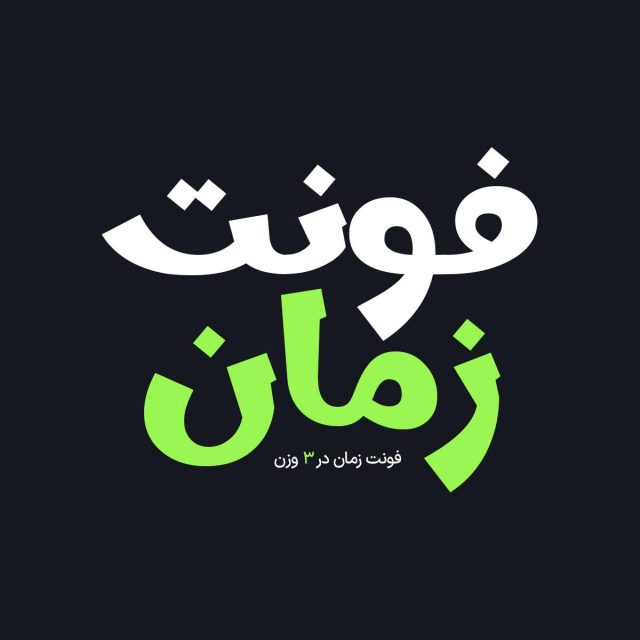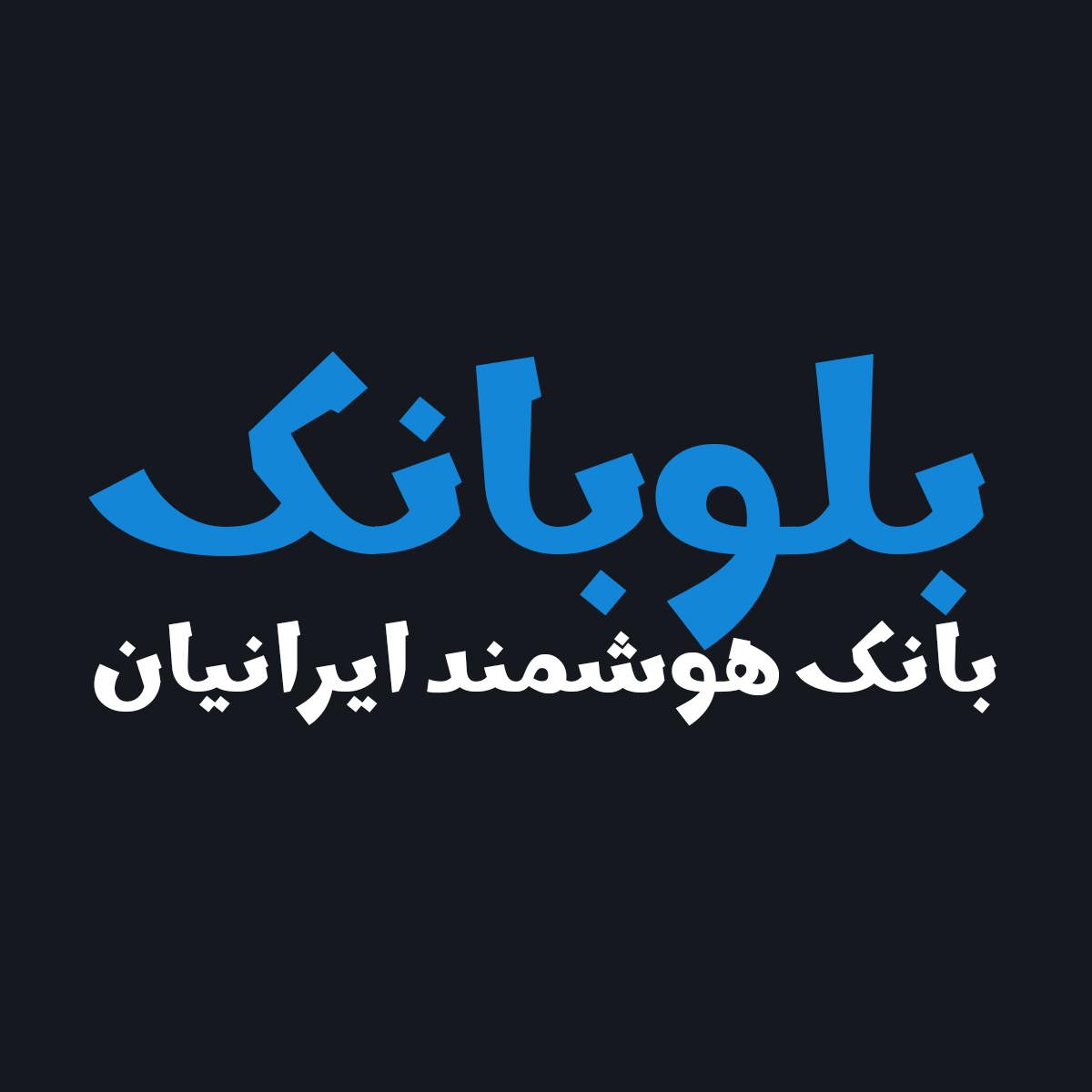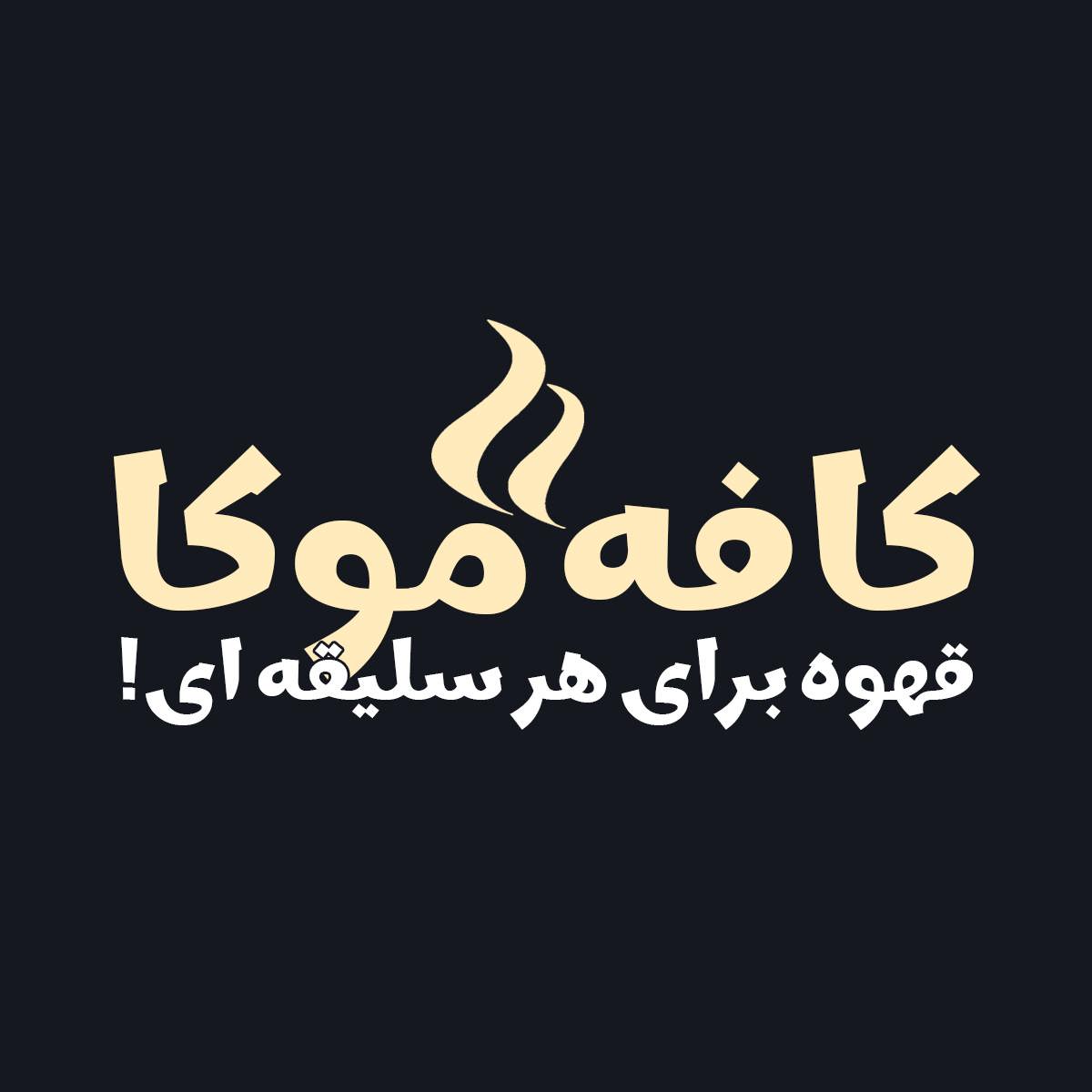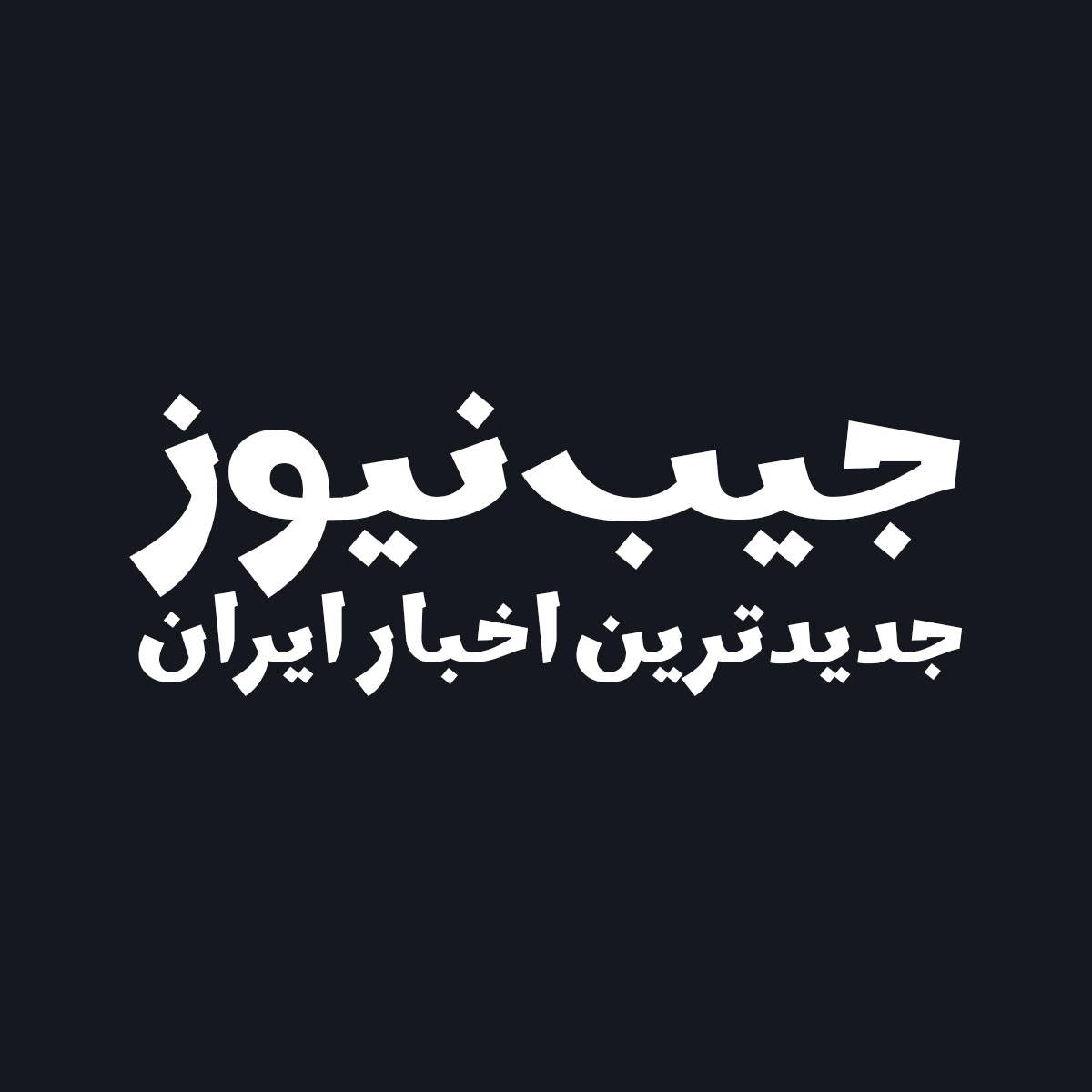
فونت فارسی زمان Zaman Font
فونت فارسی زمان یک فونت فارسی بر مبنای حروف هندسی و خاص می باشد که به طراحان گرافیک امکان خلق طرح های زیبا و حرفه ای به سادگی یک تایپ میدهد.
فونت زمان شامل 3 وزن و دارای منحنی‌های بسیار گرد با پایانه های بسیار تیز است که این خانواده فونت را زیبا، دوستانه، مدرن و خوانا می‌کند. فونت زمان با ارتفاع بالاتر از سایر فونت‌های کلاس خود طراحی شده و برای متن‌های طولانی، اندازه‌های کوچک و صفحه نمایش بهینه شده است تا خوانایی در ابعاد کوچک را در هر شرایط استفاده به ویژه برای فضای وب و صفحات دیجیتال واضح‌تر کند.
• مناسب طراحی بسته بندی ها و چاپ
• فونت ویژه تبلیغات محیطی
• فونت طراحی کاور اینستاگرام
• فونت حرفه ای برای تولید محتوا
• فونت فارسی طراحی وبسایت
• فونت طراحی لوگو تایپ فارسی
• مناسب استفاده در تابلو های چلنیوم و طراحی حروف
پیشنمایش و نمونه تایپ های فونت زمان